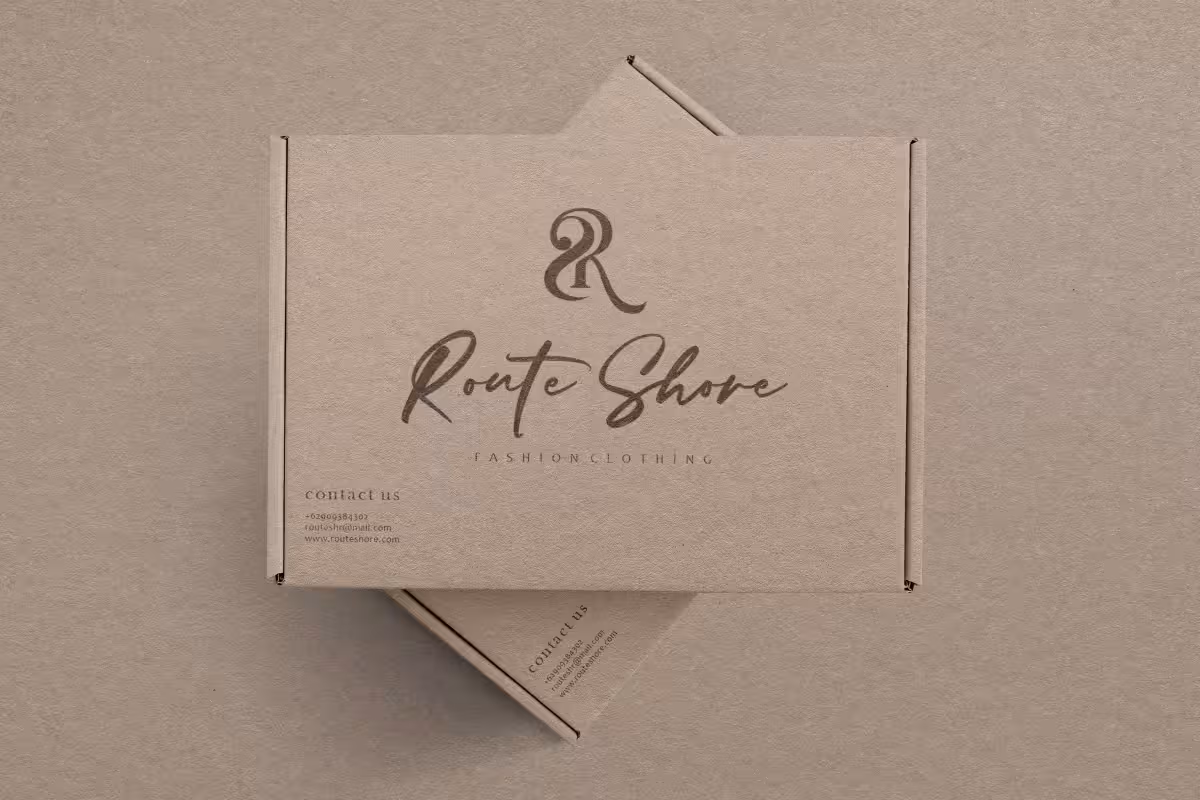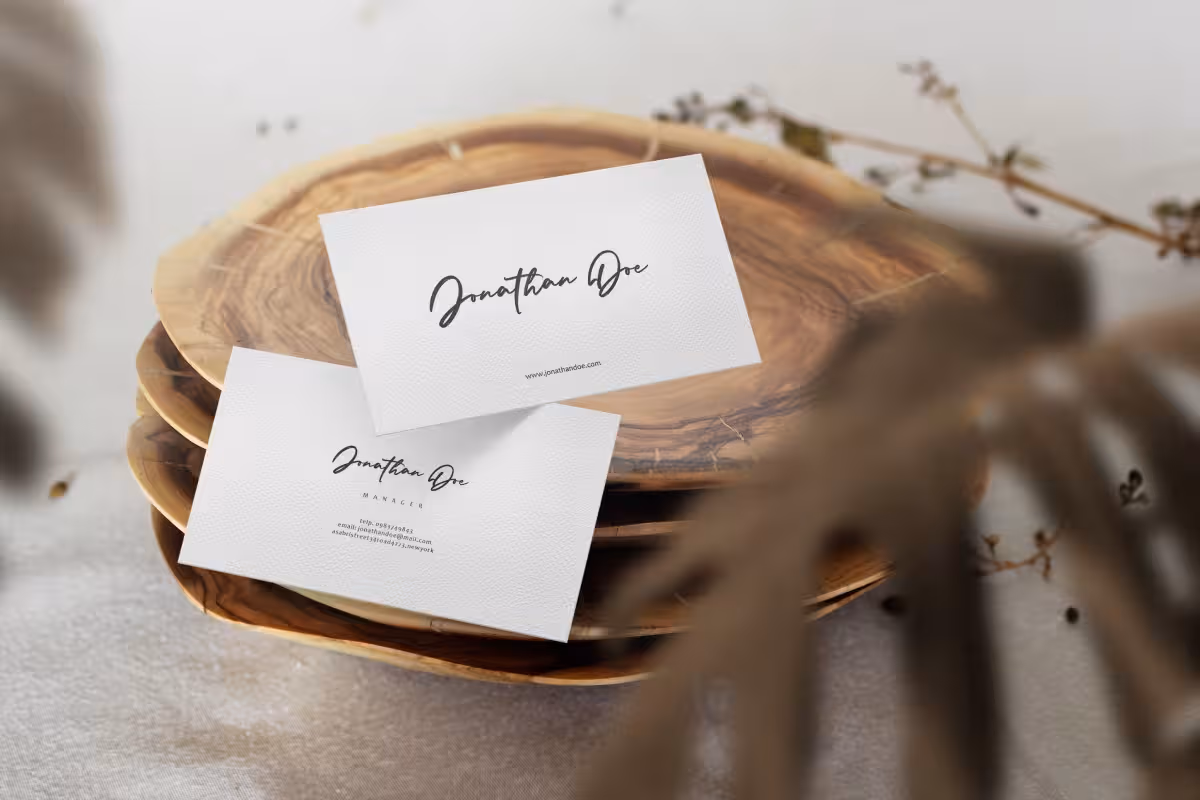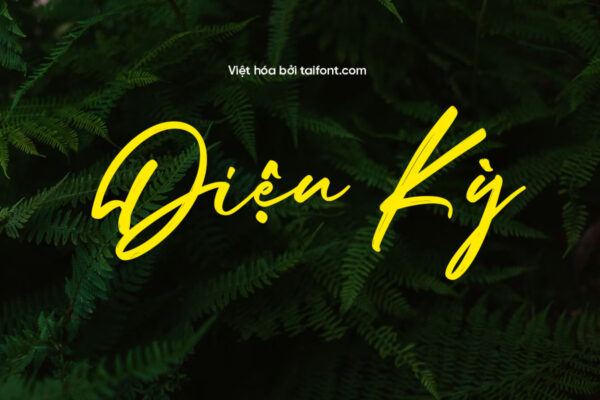
Giới thiệu về Font TF Soul Collections Việt hóa
TF Soul Collections Việt hóa là một font chữ brush (kiểu cọ) nổi bật với vẻ đẹp tinh tế, bay bổng và đậm chất thư pháp. Font này mang đến cảm giác như những nét vẽ tay được thực hiện một cách phóng khoáng nhưng vẫn rất tỉ mỉ và có hồn, toát lên sự nghệ thuật, lãng mạn và đầy cảm xúc. Soul Collections là lựa chọn lý tưởng để tạo điểm nhấn độc đáo và truyền tải một thông điệp có chiều sâu.
Với sự duyên dáng trong từng đường nét và tính thẩm mỹ cao, Soul Collections là lựa chọn hoàn hảo cho các thiết kế muốn truyền tải sự tinh tế, nghệ thuật và sự cá nhân hóa:
- Thiết kế mang phong cách thư pháp: Hoàn hảo để sử dụng cho các dự án nghệ thuật, thiệp mời, thiệp chúc mừng, hoặc các ấn phẩm cần sự bay bổng và độc đáo. Font này giúp tạo không khí lãng mạn, tinh tế và đầy cảm hứng.
- Thiết kế thời trang và mỹ phẩm: Lý tưởng cho các nhãn hiệu muốn truyền tải sự sang trọng, tinh tế và một chút phong cách thủ công. Font có thể dùng cho logo, bao bì sản phẩm, hoặc các chiến dịch quảng bá, đặc biệt là những sản phẩm nhấn mạnh tính nghệ thuật và cá nhân.
- Thiết kế ấn phẩm văn hóa, nghệ thuật: Phù hợp cho các catalogue triển lãm tranh, poster sự kiện nghệ thuật, hoặc bìa sách văn học, giúp truyền tải chiều sâu và tính nghệ thuật của nội dung.
- Trích dẫn và slogan: Tuyệt vời để tạo các câu trích dẫn đầy cảm hứng, slogan hoặc các dòng chữ cần sự nổi bật và mang tính biểu cảm trên mạng xã hội hoặc các ấn phẩm khác.
Với TF Soul Collections Việt hóa, bạn có thể dễ dàng thổi hồn nghệ thuật, sự tinh tế và vẻ đẹp thư pháp vào các thiết kế, tạo ra những sản phẩm không chỉ đẹp mắt mà còn đầy cảm xúc và sức hút đặc biệt.
Font Việt hóa TF Soul Collections – Phong chữ brush